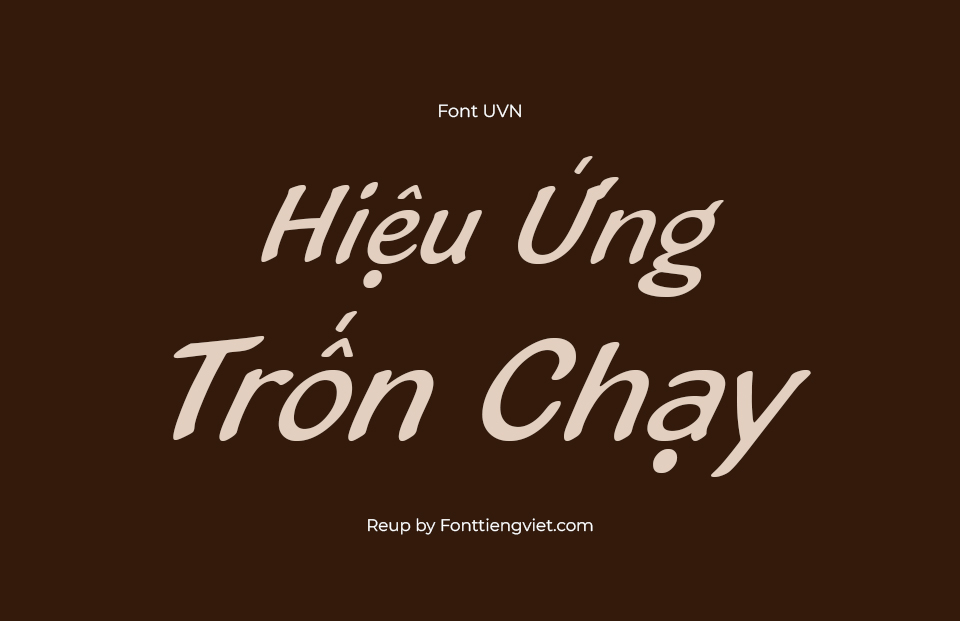
Font Việt Hóa UVN Vung Tau – Bộ Chữ Đẹp Cho Thiết Kế Việt
Giới thiệu về Font Việt Hóa UVN Vung Tau
Trong thế giới đồ họa, việc lựa chọn một Font Chữ phù hợp đóng vai trò quyết định đến tính thẩm mỹ của sản phẩm. Font Việt Hóa UVN Vung Tau là một trong những bộ font nằm trong hệ thống UVN nổi tiếng, được thiết kế tối ưu cho người Việt. Với những đường nét thanh mảnh nhưng không kém phần chắc chắn, bộ font này mang lại cảm giác hoài cổ pha lẫn hiện đại. Đây là lựa chọn lý tưởng cho những ai đang tìm kiếm sự chỉn chu trong trình bày văn bản hoặc thiết kế biểu ngữ học đường.
Đặc điểm nổi bật của Font Việt Hóa UVN Vung Tau
Ứng dụng trong giáo dục và đời sống
Nhờ phong cách trang nhã, bộ font này thường xuyên xuất hiện trong các bài thuyết trình, thiệp mời và tiêu đề báo tường. Sự rõ ràng của từng ký tự giúp học sinh dễ dàng tiếp cận nội dung, đồng thời tạo nên sự đồng bộ chuyên nghiệp cho các tài liệu giảng dạy của thầy cô giáo.